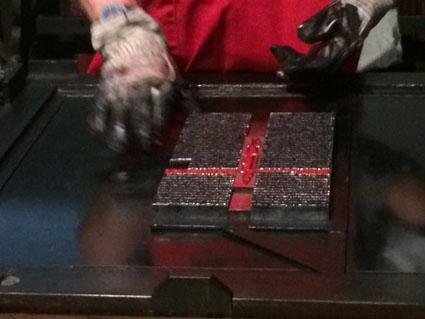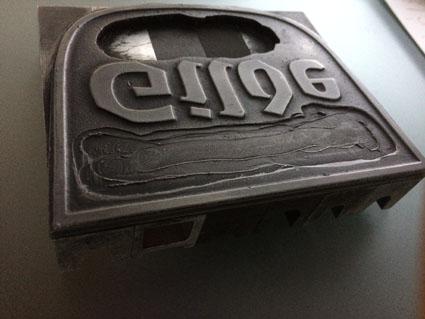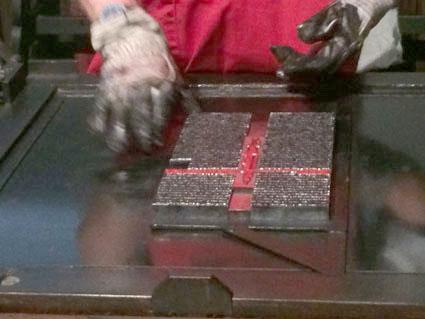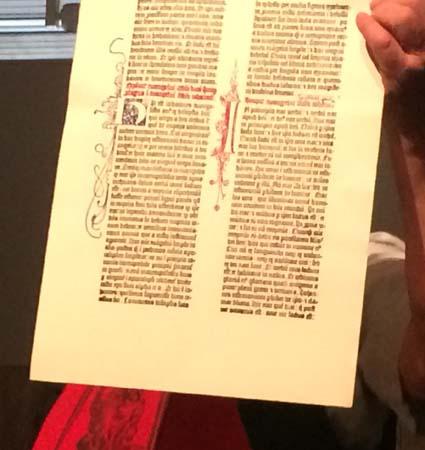
Ausstellung: Ohne Zweifel Gutenberg?
Das Gebäude mitten in der Stadt Mainz schenkt Johannes Gutenberg einen sehr würdigen Platz. Aber drinnen? Insgesamt finde ich das Museumskonzept sehr verstaubt und wenig inspirierend - aber das ist natürlich eine sehr subjektive Bewertung.
Wenn allerdings fachlich-sachliche Unkorrektheiten die lieblose Darstellung begleiten, erzeugt das bei mir eine wirkliche Empörung.
Die personengeführte Druckpräsentation
Der präsentierende Herr sprach vom "Klischee", das er nun wie zu Zeiten Gutenbergs drucken wird. Das "Klischee" hat in der Drucktechnik eine völlig andere Bedeutung. Auf meine Frage hin erfuhr ich, dass der Begriff Klischee korrekt sei.
Ohne Erklärung blieb der Umstand, dass der präsentierte Druck nicht mit Einzellettern (der zentralen Erfindung Gutenbergs!) sondern in vier Einzelblocks (Schrift/schwarz) plus Schmuckelementen/rot geschah.
Die präsentierte Zweifarbendrucktechnik (Druckstöcke/schwarz mit Schmuckelementen/rot) als gleichzeitiger Druckprozess geht meiner Ansicht nach völlig an der Realität vorbei. Nähme man aus einer gesamten, geschlossenen Form die rot zu druckenden Elemente heraus, die Lettern aus der Kolumne würden stürzen, die Satzform zusammenfallen. Der Druck erfolgte mit Sicherheit zweistufig, in der ersten Stufe mit der Schwarzform, danach mit der Rotform.
Präsentation einzelner Buch-Exponate
Es gibt bessere Lichtkonzepte empfindlicher Bücher, so zu sehen im Stift Admont, das ebenfalls wertvolle Bücher aus dem Gutenberg-Zeitalter präsentiert.
Dass aber die Bücher in Vitrinen zum Teil flach präsentiert werden und nicht geneigt, ist nicht nachvollziehbar. Das genaue Betrachten wird unmöglich gemacht und ist völlig unnötig.
Entwicklung der Handschriften
Die eigentlich schöne Idee, seinen Namen in den verschiedenen historischen Handschriftarten auf die Kunststoffläche zu schreiben scheitert daran, dass kein Stift vorhanden ist.
Römische Schrift
Es ist wissenschaftlich unseriös, wenn die Reproduktion der Schrift mit "pompejanische Wandkritzelei" betitelt wird.
Koreanische Schrift
Beschrieben wird die Entwicklung koreanischer Einzellettern, bzw. characters mit Zeitangabe. Doch was wird an der Wand präsentiert? Komplette Einzelzeilen (wie Linotype), keine Einzelelemente!
Chinesische Einzellettern (bzw. characters)
Die Präsentation verweist auf keine Jahresangaben.
Das ist lediglich ein Auszug meiner Kritikpunkte, da ich keine Aufnahmen machen durfte (völlig korrekt) oder Notizen machen konnte, habe ich mir die weiteren Kritikpunkte nicht merken können, aber ich glaube, die oben aufgeführten reichen aus, um meine Enttäuschung deutlich zu machen.
Fazit
Dieses Museumskonzept stellt für mich eine historisch geringschätzende Präsentation Gutenbergs Leistung und Bedeutung dar. Sehr schade.
Reproduktion der Schrift
Welcher Schrift denn präzise? In Pompeii hat man ja schon so einiges gefunden, dass ob seiner Obszönitäten in früherer Zeit durchaus als Gekritzel bezeichnet wurde.
Gutenberg hat, soviel ich weiß, mit rotem Druck experimentiert. Das Drucken der roten Typen war aber zu umständlich und wurde wieder aufgegeben. Die rote Farbe wurde von den Rubrikatoren eingezeichnet. Am Buch des Mittelalters arbeiteten neben Setzern, Druckern und später Buchbindern auch Rubrikatoren und die Illustratoren zur »Illumination« der Texte. Wie bei Gutenberg rot gedruckt wurde, weiß ich nicht. Vielleicht hat man in einem zweiten Arbeitsgang gedruckt, man hätte aber auch die rot zu druckenden Typen aus dem Satz nehmen, einfärben und wieder einstecken können. Das ist sicherlich bekannt und nachzulesen, denn den Drucken, sofern sie vorhanden sind, was ich annehme, weil man sonst kaum davon wüßte, könnte man die Arbeitsschritte ansehen.
Eine schräge Buchpräsentation kann Nachteile für das Buch haben, zumal wenn es groß und schwer ist. Die Draufsicht in flachen Vitrinen gestattet auch eine plane Lage. Das schummrige Licht stört mich öfter in solchen Ausstellungen, aber ich nehme an, daß es nicht anders geht, will man den Zustand der Werke nicht beeinträchtigen. Es ist ja auch in der ganzen Bildkunst nicht mehr möglich, alte Arbeiten in natürlichem Licht zu sehen, was ihnen sicherlich viel von ihrem Reiz nimmt, zumal weil Farben mit wechselndem Licht arbeiten. Wer Bilder in altmeisterlicher Ölmalerei in Privatbesitz anschauen kann, kennt das Spiel mit dem Licht. Aber in der Abwägung im Museum steht der Erhalt immer im Vordergrund.
Sicherlich im umgangssprachlichen Sinn. Die Herkunft des Wortes Klischee aus der Drucktechnik kennen die meisten Leute nicht. Ich stolperte allerdings in dem Bericht über die Vorführung über das Zusammenbringen von Gutenberg und »Klischee«, denn zu Gutenbergs Zeiten gab es meines Wissens noch lange keine Klischees, auch das Wort nicht.
Sicherlich im umgangssprachlichen Sinn.
Sicherlich nicht. Der Kontext war:
Der präsentierende Herr sprach vom "Klischee", das er nun wie zu Zeiten Gutenbergs drucken wird.
Wenn eine Fachdefinition gegebenen werden würde, könnte man prüfen, ob man dieser grundsätzlich und im konkreten Kontext zustimmt. So wird bislang nur unprüfbar in den Raum gestellt, dass die Museumsleute vermeintlich falsche Dinge verbreiten.
Wir hatten aber entweder von zwei Formen mit Anlegevorrichtung gedruckt, oder aber mit schmalen Walzen die vorher abgewischten Zeilen eingefärbt. dazu gehörte sicher einiges an Übung. Es kam immer auf die Form des Satzes an, welche Methode zur angewandt wurde.
Die Zeilen ziehen und einfärben kann ich mir bei großen Schriftgraden ev. vorstellen, trotzdem würde ich eine passende kleine Walze vorziehen.
Es gibt und gab immer mehrere Methoden um ans Ziel zu kommen. Methoden an die sich vielleicht heute keiner mehr erinnert.